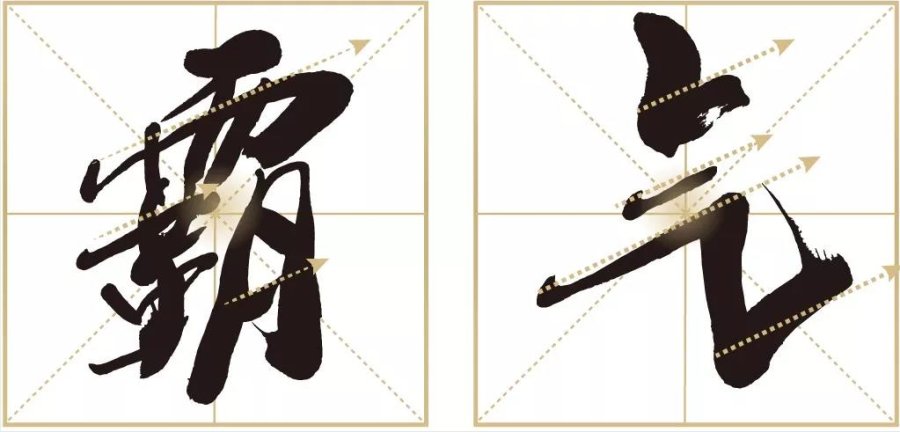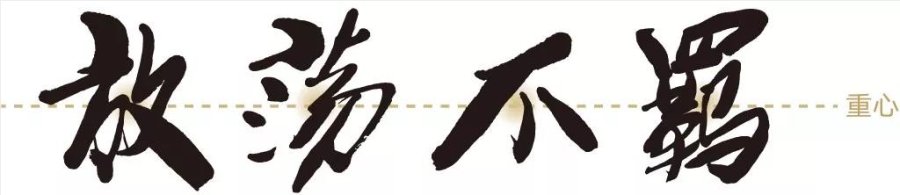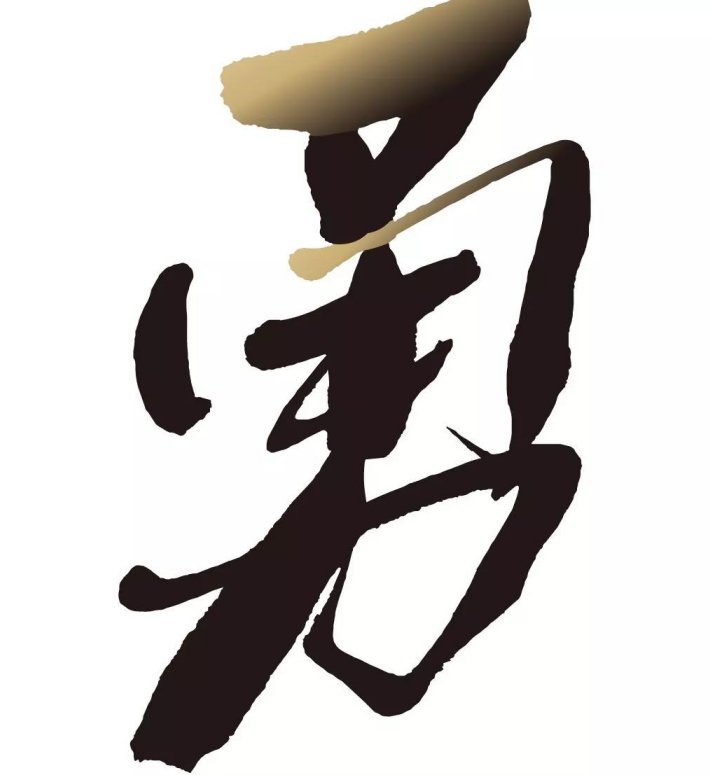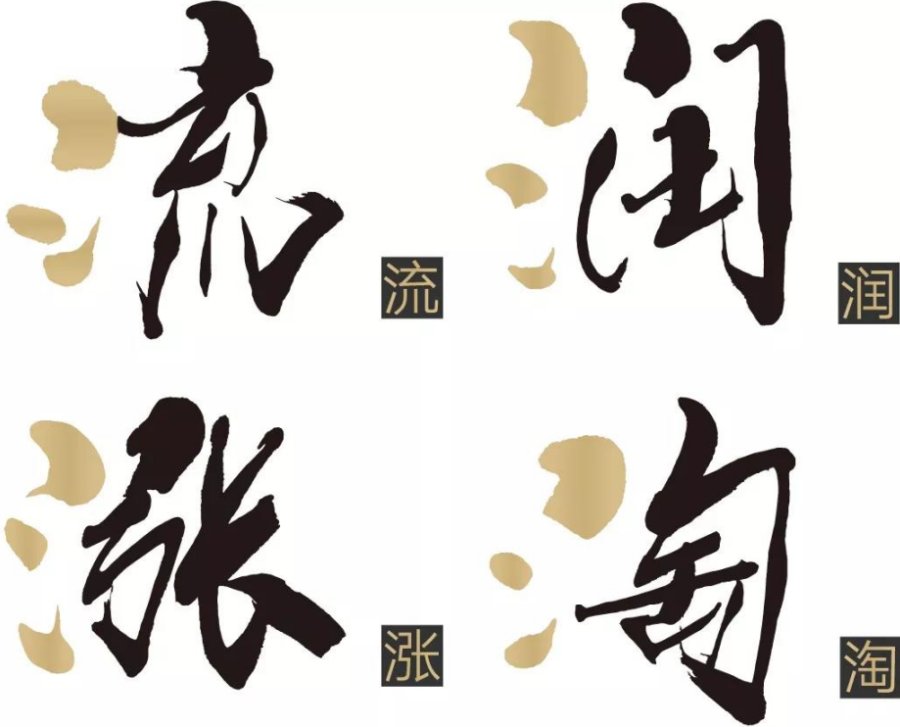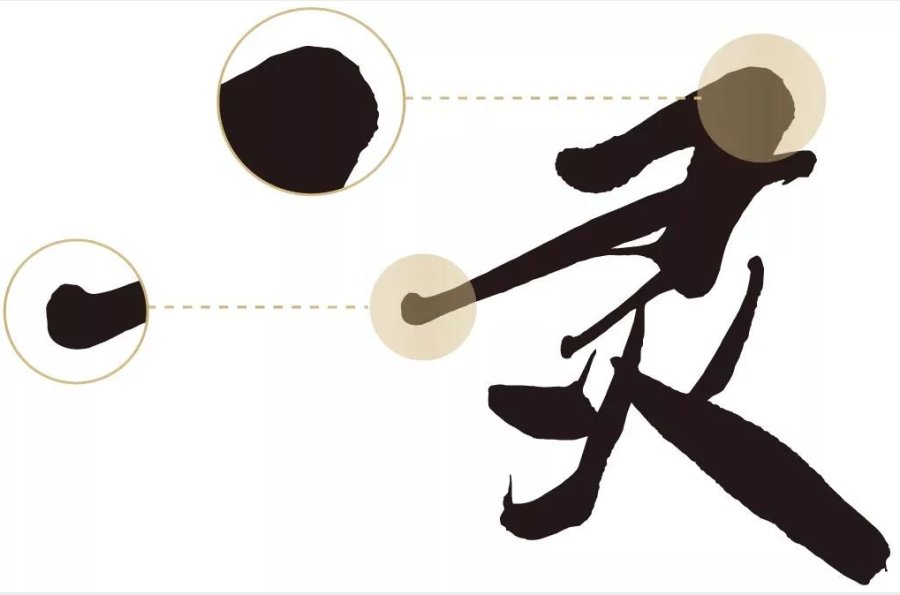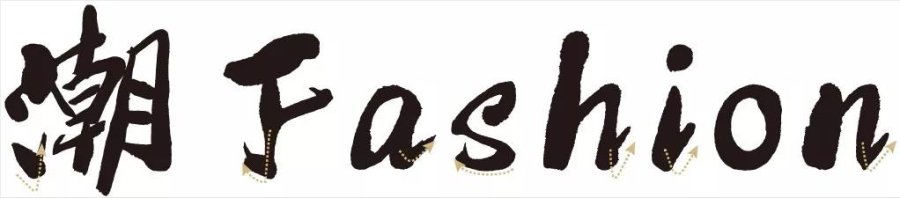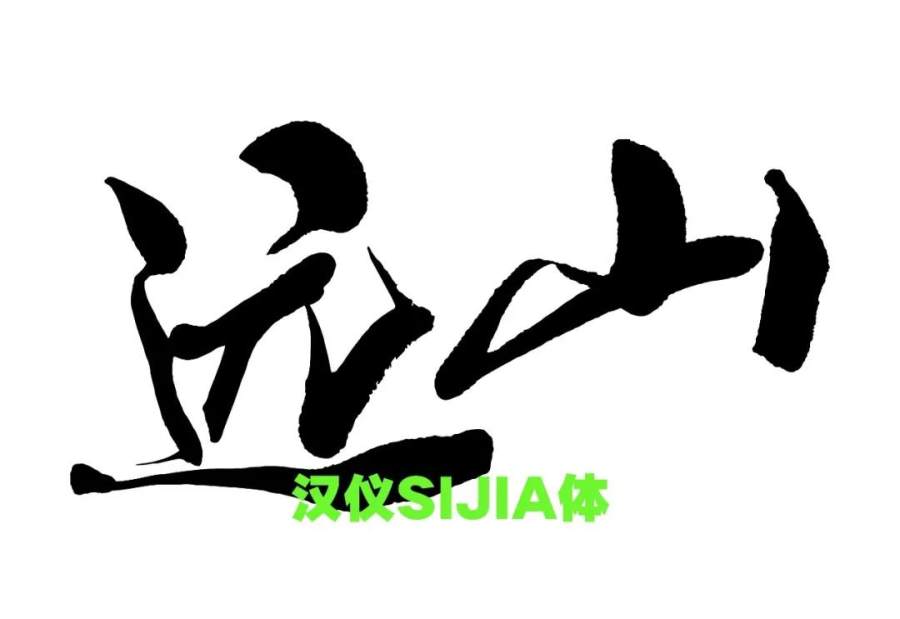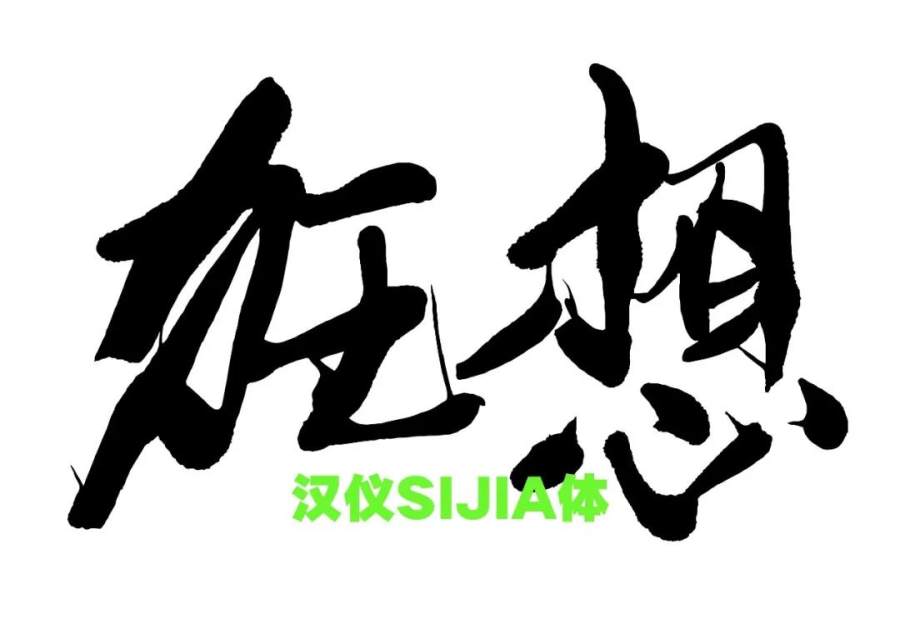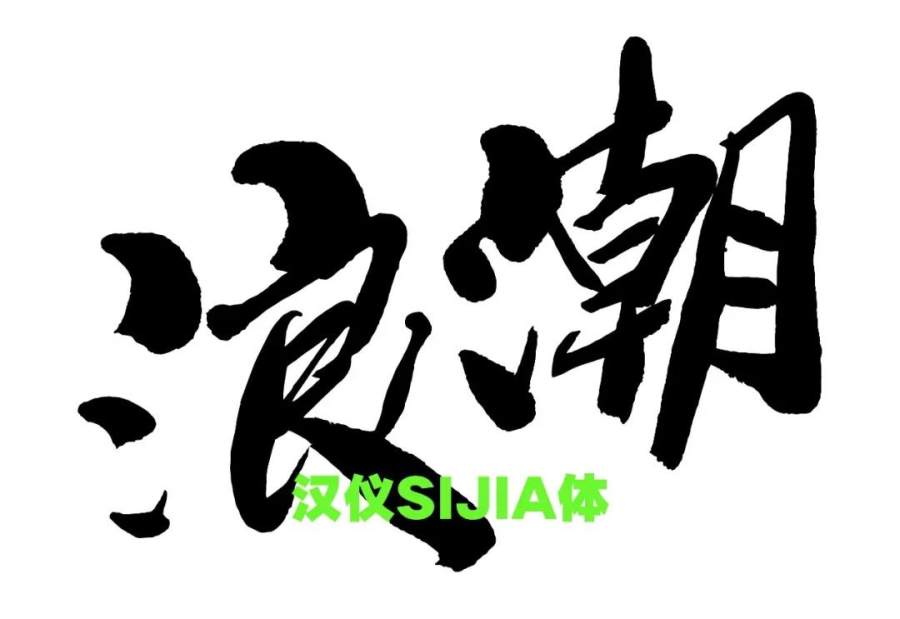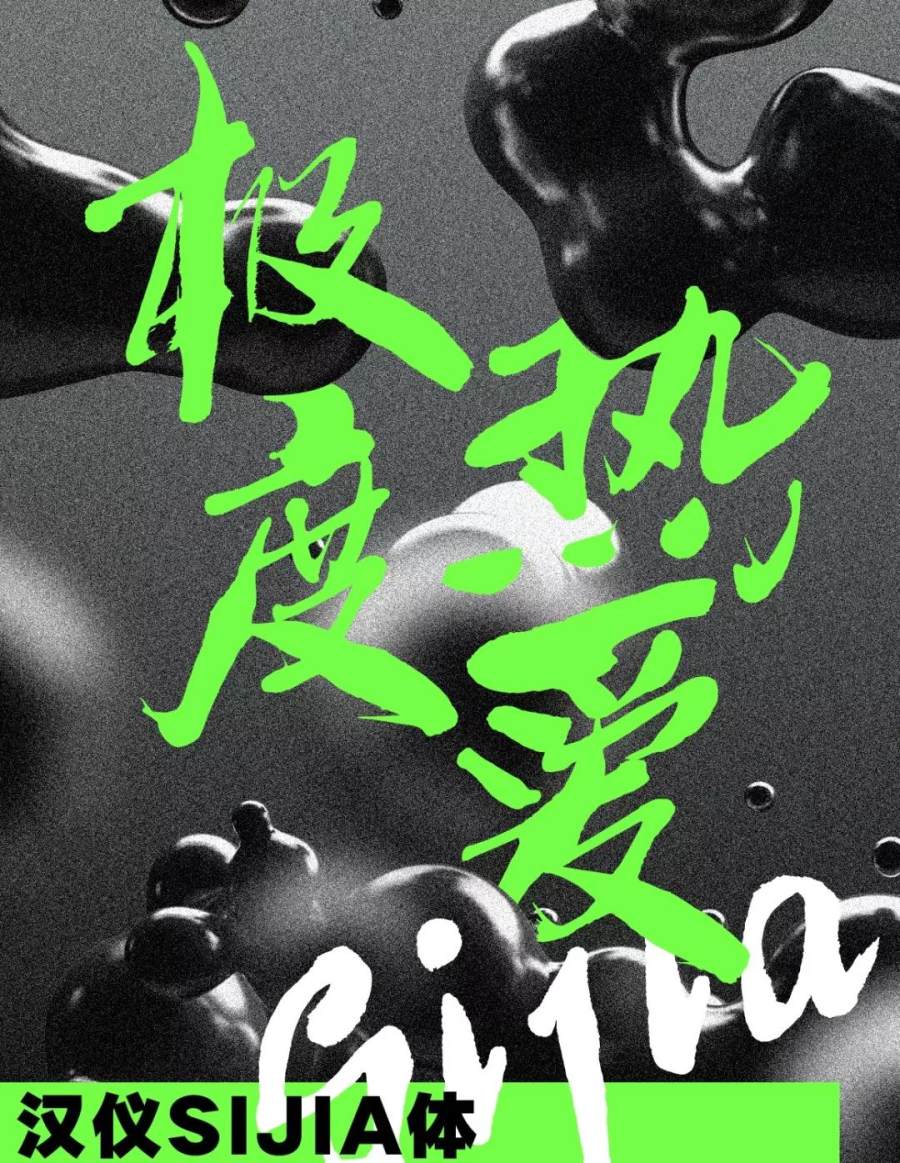
汉仪SIJIA体 | 字形特点
汉仪SIJIA体,字迹飞扬,字形统一,均向右上方倾斜的横画笔势,
增强了其排版效果的力量感和节奏感。
汉仪SIJIA体 | 字形特点
汉仪SIJIA体字形斜中求稳,重心一致,这使得其在组合排版使用时效果更佳。
汉仪SIJIA体 | 笔画特点
汉仪SIJIA体,笔画粗细对比明显,组合搭配富有强烈的节奏感。
汉仪SIJIA体 | 笔画特点
汉仪SIJIA体,结体俊逸自如,字的笔画根据不同位置作出灵活多样性的改变。
下笔收笔,起承转合,多顺势而为,潇洒多姿。
汉仪SIJIA体 | 笔画特点
汉仪SIJIA体,起笔有停顿,点画饱满,转折圆润,新颖时尚,强烈的王思佳个人风格,贯穿了字体的转折笔画间。
汉仪SIJIA体 | 西文字母
汉仪SIJIA体西文字母的设计,参考并借鉴了中文笔画的书写方式,
较好的还原了书法的手写体感觉,使中西文的搭配和谐统一。
汉仪SIJIA体 | 应用展示
汉仪SIJIA体将传统书法与现代设计完美融合,
集博大深沉的书法文化与时尚潮流于一体,
既拥有文学艺术涵养,又有着前卫的创造力,适用于各类商业包装。